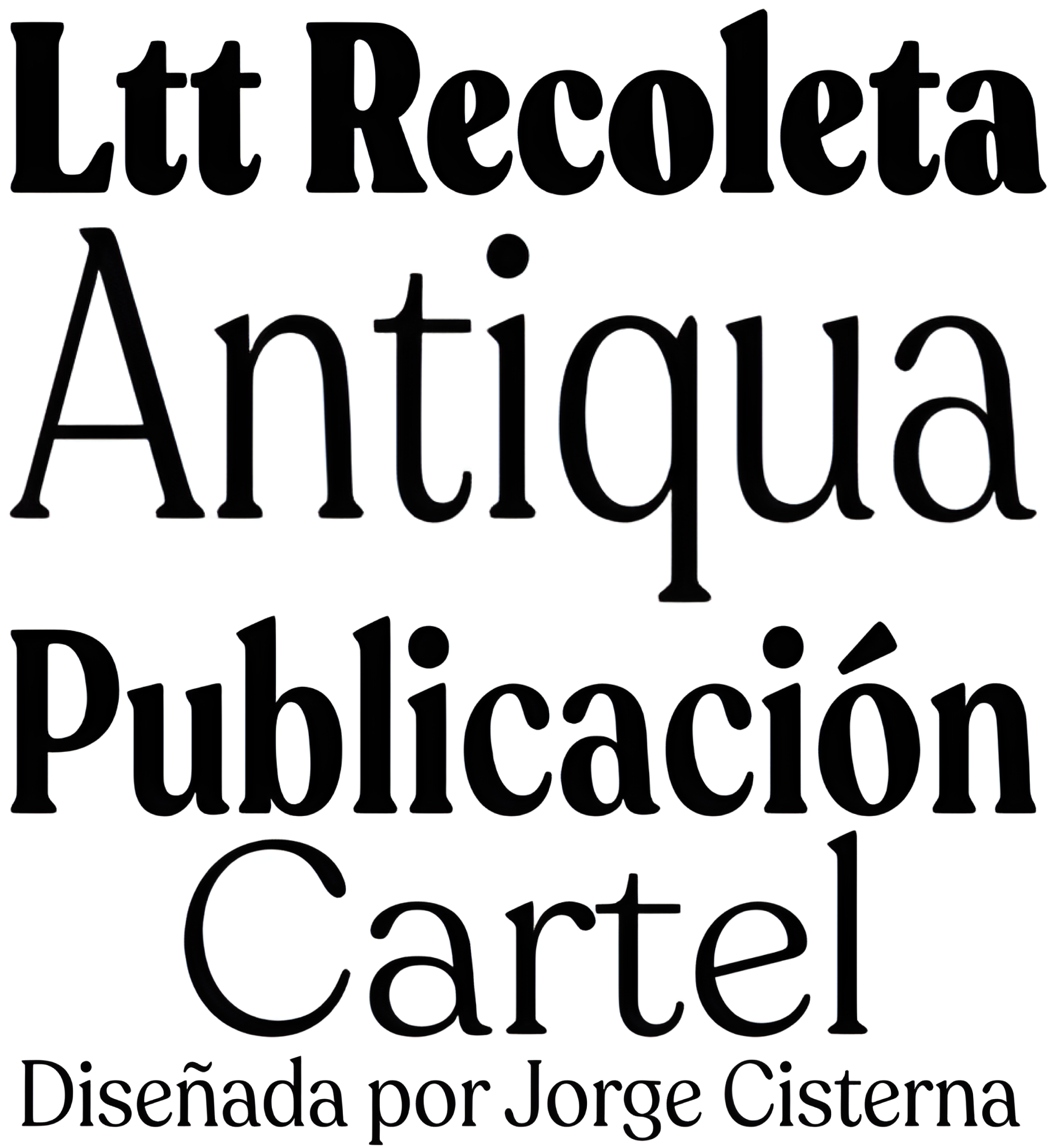
| Créditos | Jorge Cisterna |
| Descripción | Esta nueva Recoleta se compone de 24 estilos en total. A su anchura clásica hemos añadido dos nuevas variantes con dos grados diferentes de condensación: una muy condensada y esbelta, y otra en el punto medio entre la anchura estándar y la condensada. |
| Familia(s) | Ltt Recoleta |
| Estilos | 24 |